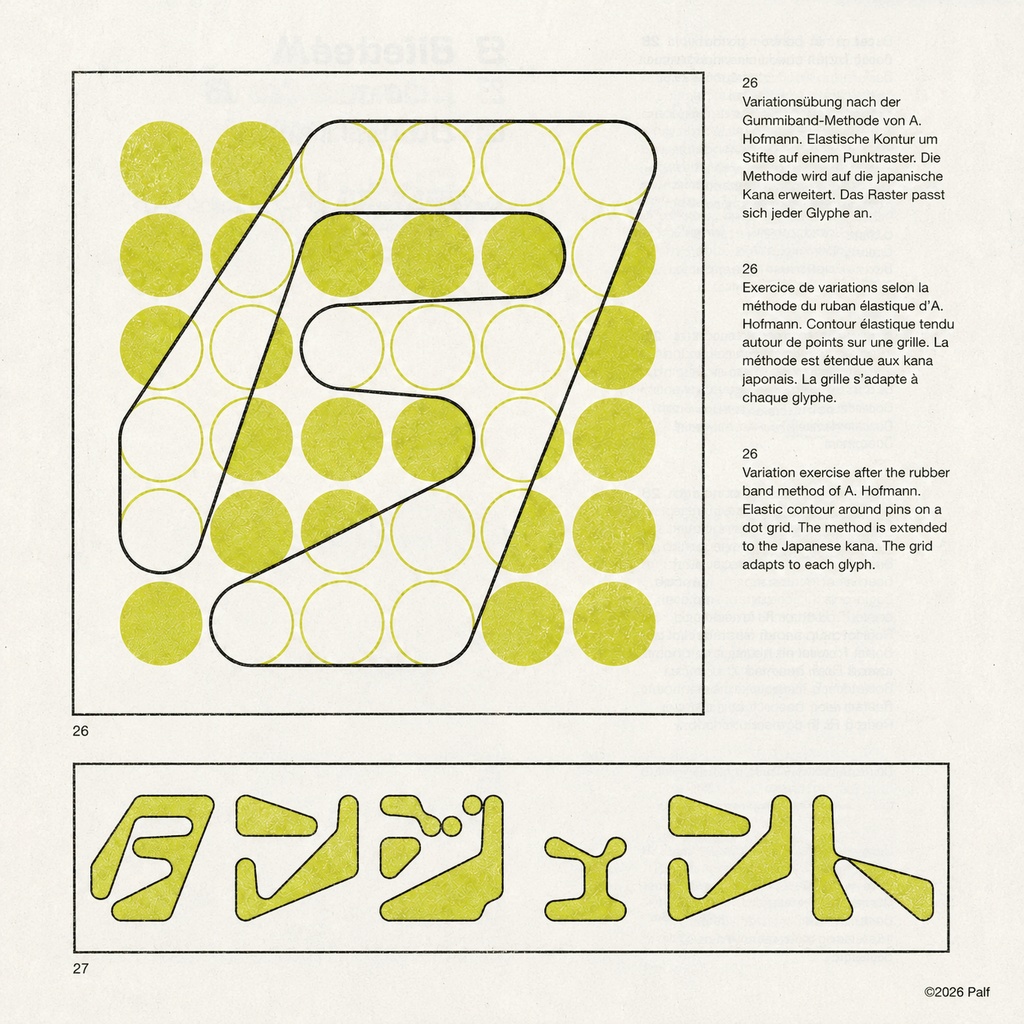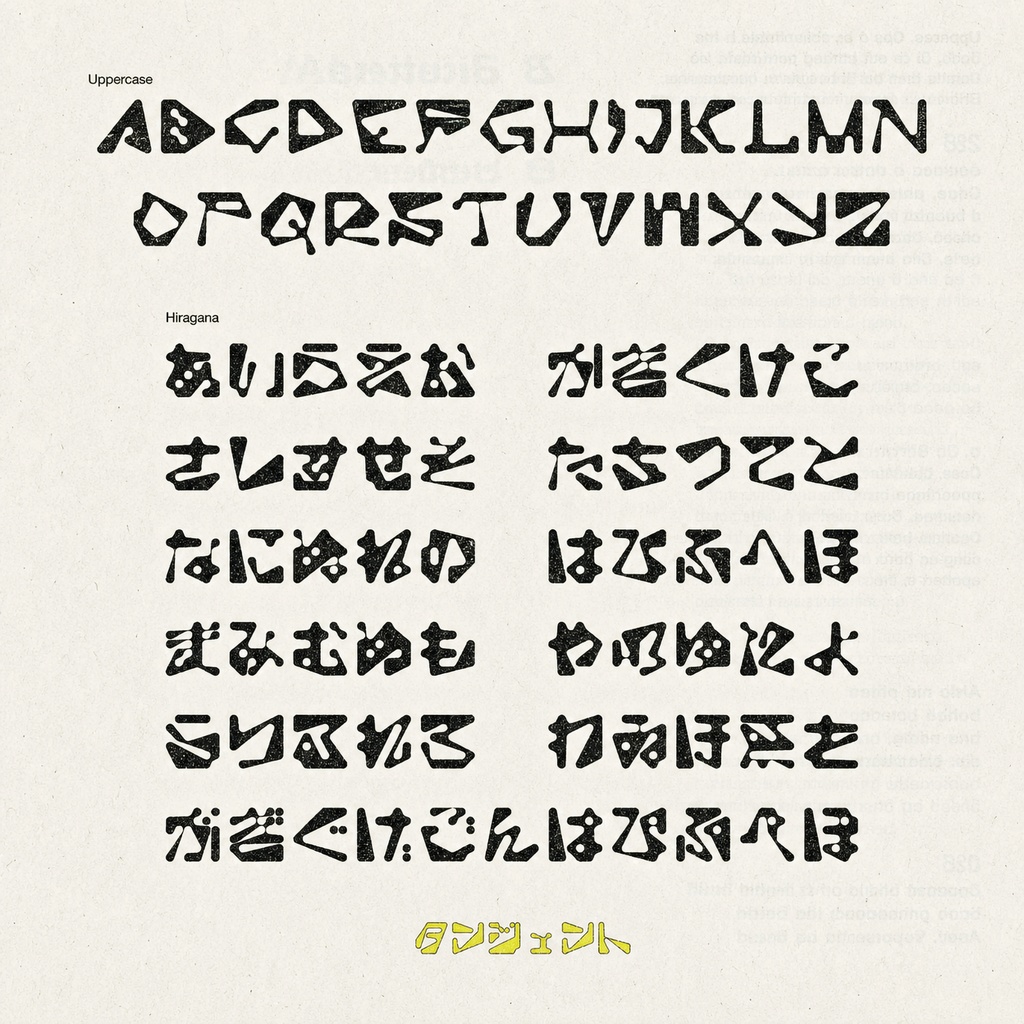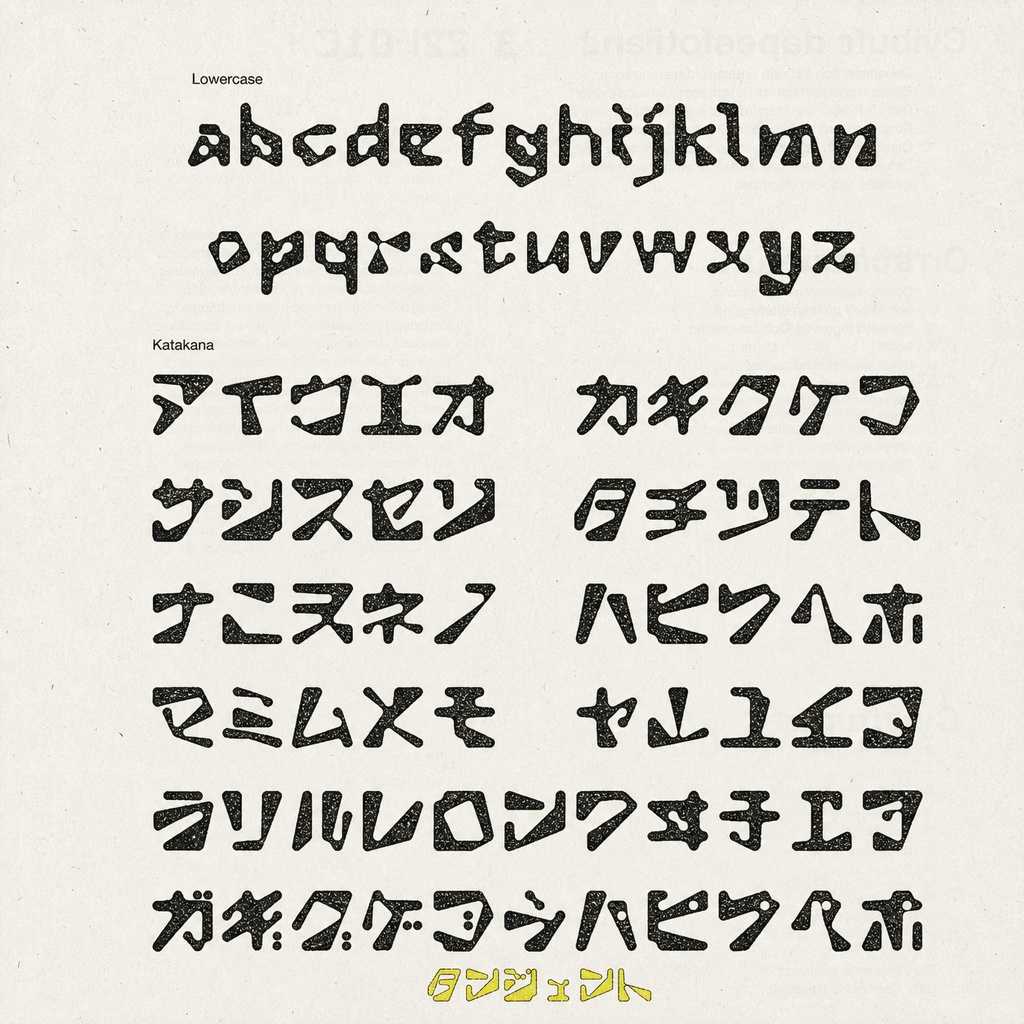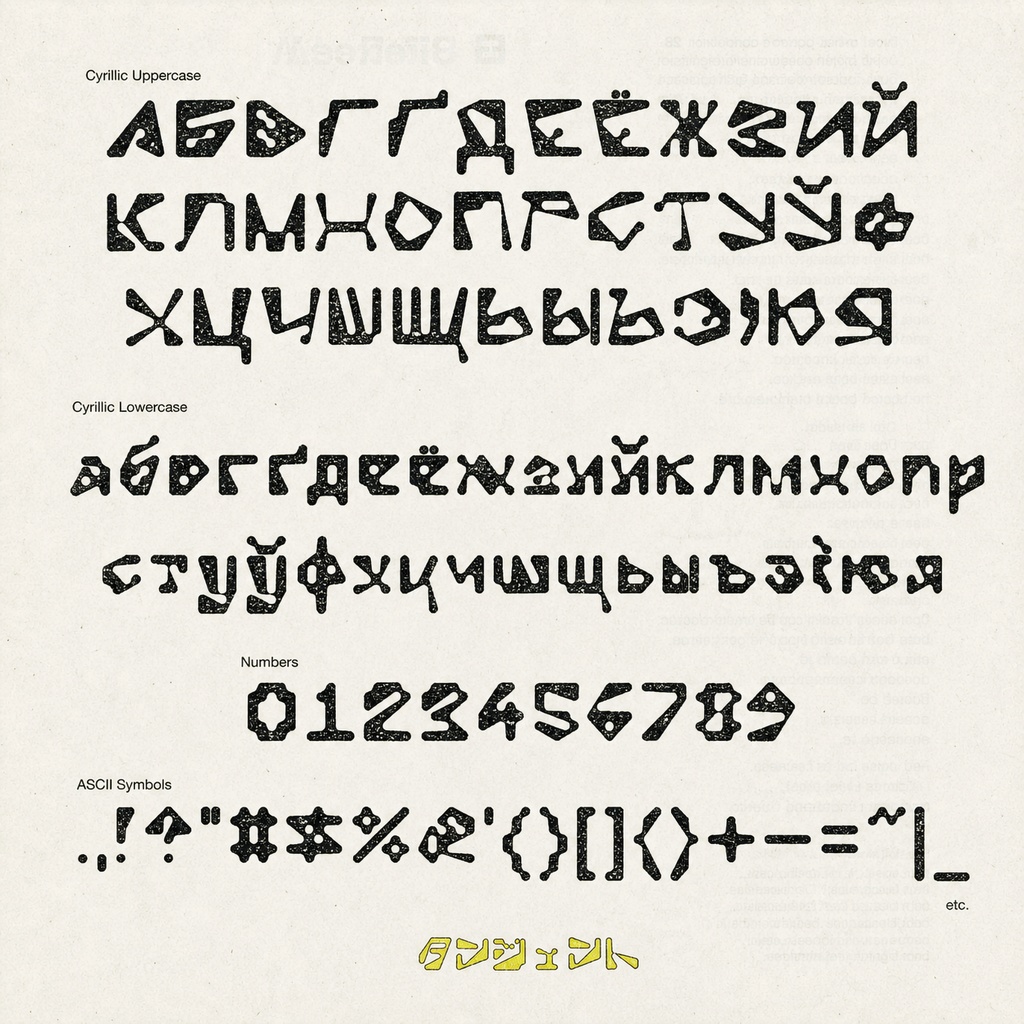
タンジェント【フォント】
アーミンホフマンが考案したグリッドシステムに由来するフォントです。 目を引く奇抜な印象があるのでタイトルなどにどうぞ。 【フォント仕様】 ・収録文字種 基本ラテン文字/キリル文字/ひらがな/カタカナ/ASCII記号/大文字記号 743グリフ/486文字 収録 OpenTypeフォント / TrueTypeフォント 【利用規約】 当フォントをご利用された時点で、この利用規約に同意したものと見做します。 当フォントデータは、本規約に定める条件でご利用者様に使用する権利を許諾します。 当フォントの著作権やその他一切の権利はPalfに帰属します。 ●使用条件 1) 2人以上の複数人でご利用になる場合のみ、1ライセンスにつき端末3台までといたします。 2) 本フォントを使用して得られる結果については、仕様者自身が責任を負うものとします。 3) 一般印刷物の作成(ポスター、書籍、フライヤー等)にご利用いただけます。 4) 立体制作物の作成(ステッカー、Tシャツ、アクリルキーホルダー等)にご利用いただけます。 5) 映像及びWebに関連する制作物に於いては、画像化・アウトライン化した上でご利用いただけます。 6) ロゴマーク、タイトルデザインの作成にご利用いただけます。 7) 画像化・アウトライン化したものを加工・変形してご利用いただけます。 8) 購入者本人又は事務所内等での限定した使用に限り、当フォントファイルを改変し、本人のみが使用することができます。 ●禁止事項 当フォントファイルを使用する際、以下の事項を禁じます。 1) 第三者への譲渡・貸与・配布・販売 2) 当フォントデータを元とした、類似又は同一フォントのデータの作成 3) 公序良俗に反する目的、誹謗中傷目的での使用 4) 政治的・宗教的利用 5) 犯罪への利用 6) 当フォントのサーバー上へのアップロード 7) 当フォントデータを取り出すことができるソフトウェアへの組み込み ●その他 ・上記に記載されていない事項については、著作権法及び関連法規に従うものとします。 ・本利用規約は予告なしに変更されることがあります。